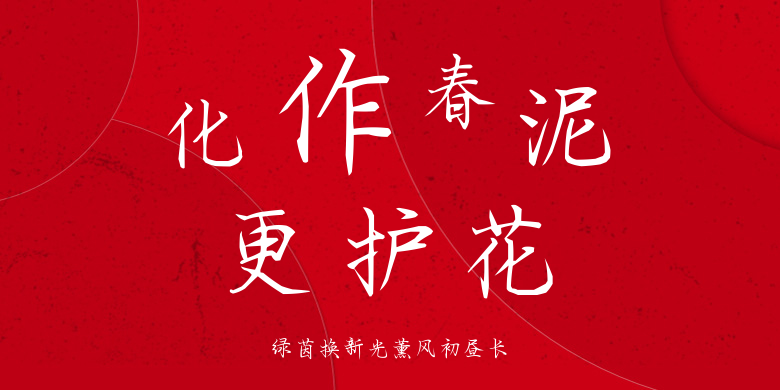
绿茵换新光薰风初昼长
绿茵换新光薰风初昼长,这款字体结构工整、笔画清晰,兼顾美观与易读性,适用于标题、正文、海报、包装、LOGO 等多种场景。字形优雅稳定,风格百搭耐看,适配日常排版与创意设计,让文字呈现更舒适、更具质感。绿茵换新光薰风初昼长一笔一画,皆是细节,以均衡的比例、流畅的线条打造舒适视觉体验,字形端正大气,风格简约现代。无论是商业设计、品牌宣传还是日常排版,都能轻松驾驭,让文字更有格调与力量。绿茵换新光薰风初昼长字体下载。